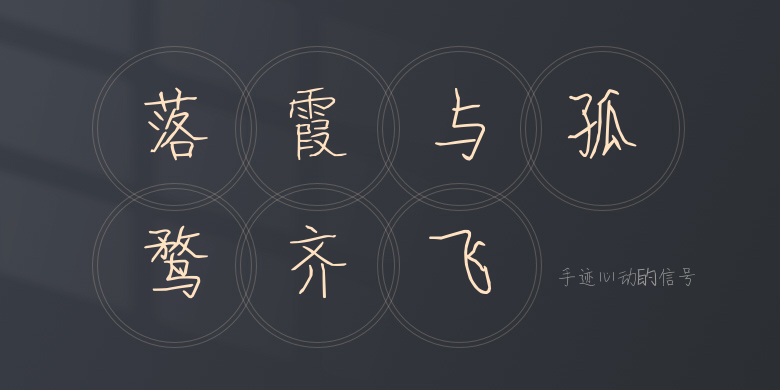
手迹心动的信号
手迹心动的信号,这款字体结构工整、笔画清晰,兼顾美观与易读性,适用于标题、正文、海报、包装、LOGO 等多种场景。字形优雅稳定,风格百搭耐看,适配日常排版与创意设计,让文字呈现更舒适、更具质感。手迹心动的信号一笔一画,皆是细节,以均衡的比例、流畅的线条打造舒适视觉体验,字形端正大气,风格简约现代。无论是商业设计、品牌宣传还是日常排版,都能轻松驾驭,让文字更有格调与力量。手迹心动的信号字体下载。